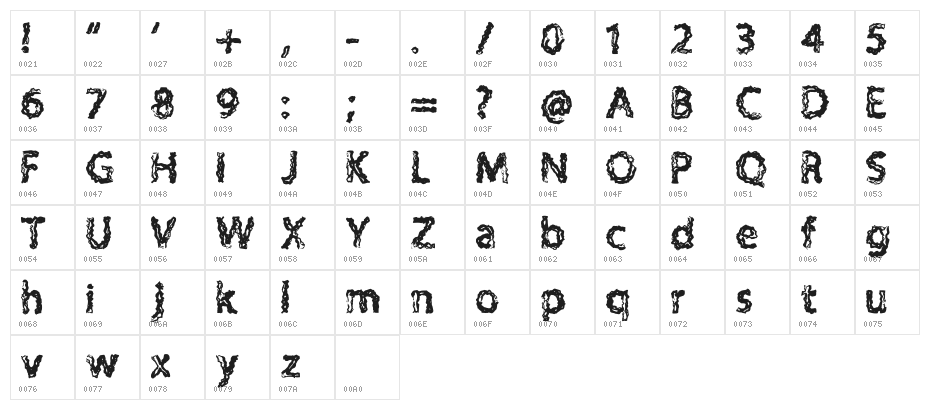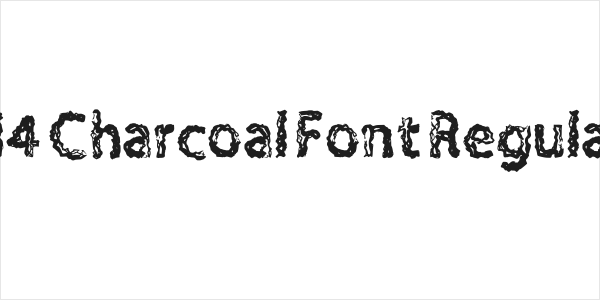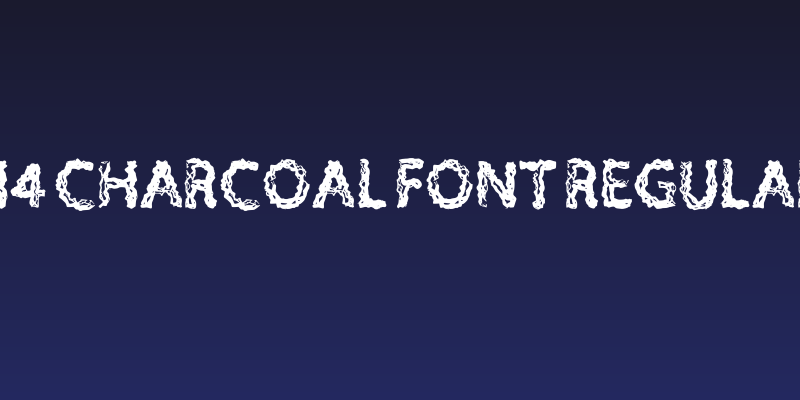
H4 Charcoal Font Regular Font
H4-CHARCOAL-FONT-REGULAR MAIUSCOLE
H4-CHARCOAL-FONT-REGULAR MINUSCOLO
H4-CHARCOAL-FONT-REGULAR ALTRI CARATTERI
| Stile generale | Artistic, Raw, Creative |
| Caso d'uso | Headlines, Posters, Artistic Designs |
| Progetti proposti | Ideal for artistic projects, posters, album covers, and any design requiring a bold, creative touch. |